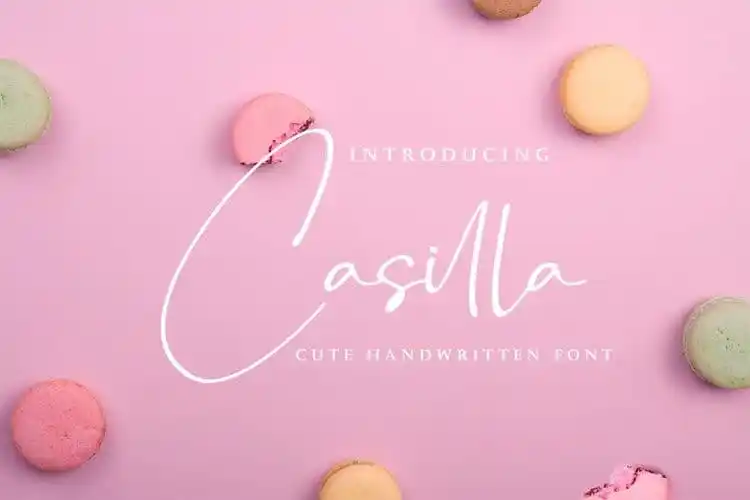
Casilla Script Font – Download Grátis
A Casilla Script Font é uma elegante tipografia para assinaturas que adicionará frescura e modernidade a qualquer projeto visual. Inspirada na autêntica escrita manuscrita, essa fonte tem um baseline dançante que cria um toque de originalidade e personalização. É perfeitamente adequada para sua identidade empresarial, design gráfico, projetos digitais sociais e até mesmo suas tarefas DIY criativas. Como resultado do trabalho meticuloso da Dav Studio, essa fonte oferece uma experiência visual agradável que será certamente bem-vinda em seu próximo projeto gráfico. Se você está procurando por uma fonte que dê vida aos seus projetos de design, esta é uma opção inteligente para considerar.